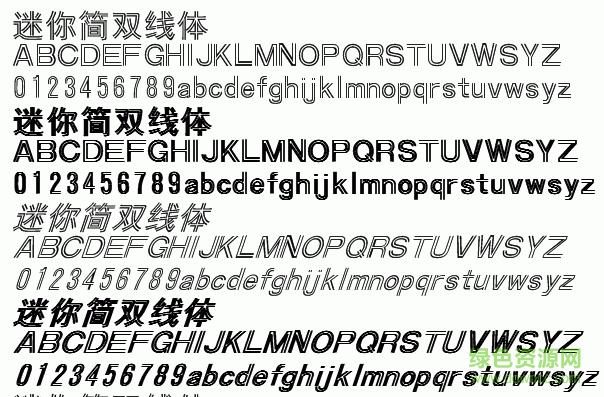
迷你簡雙線體字體
迷你簡雙線體是一款不同于一般字體的雙線形字體,為你帶來雙條線字體效果,能夠進行到視頻文字插入,也可以進行藝術(shù)字便捷,為你添加各種獨特字體效果變得更加迷人!需要的用戶快到綠色資源網(wǎng)下載體驗吧!
迷你簡雙線體介紹
迷你簡雙線體是好看的雙線體字體,這款字體是由雙線條組成的,給人的視覺效果十足。